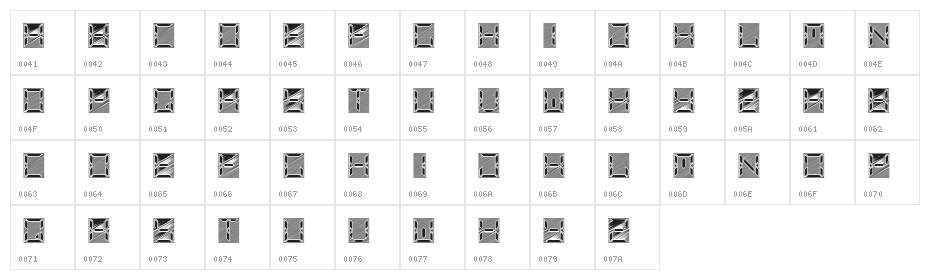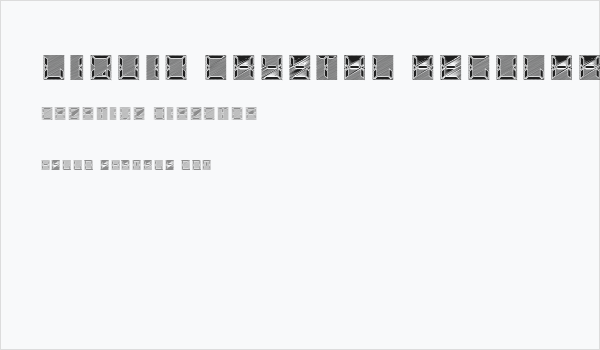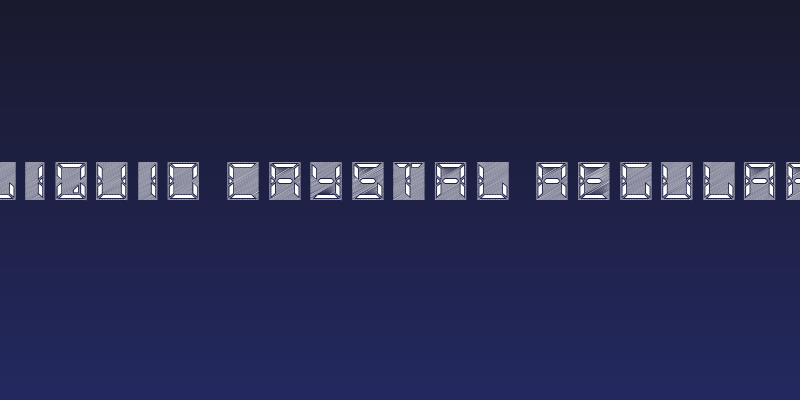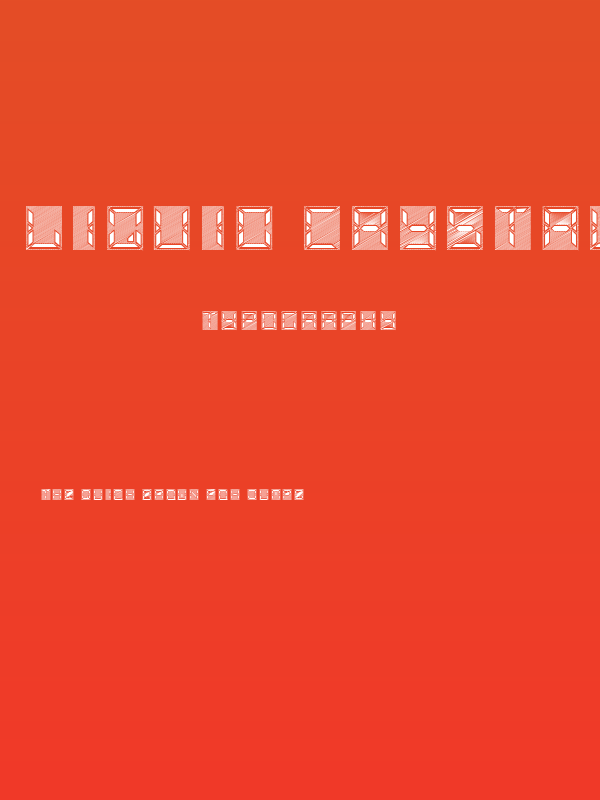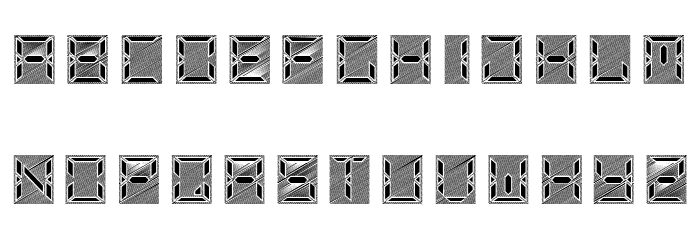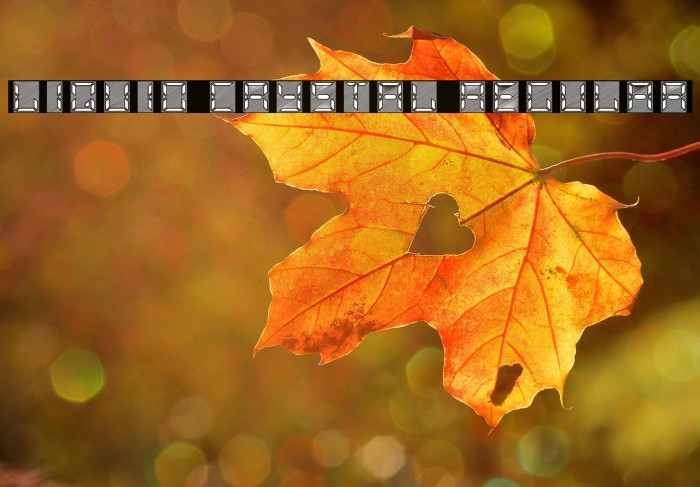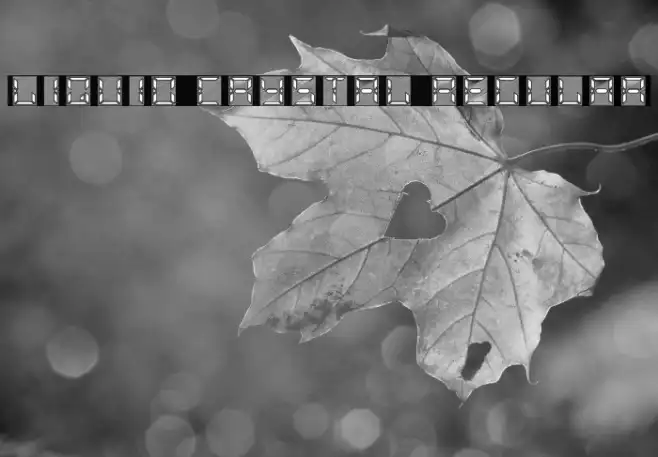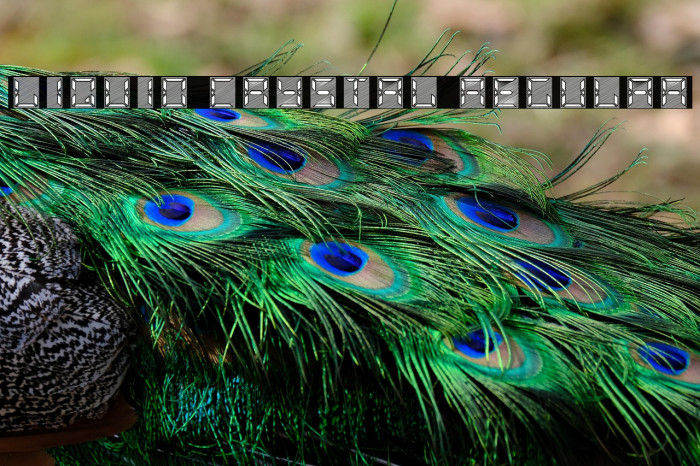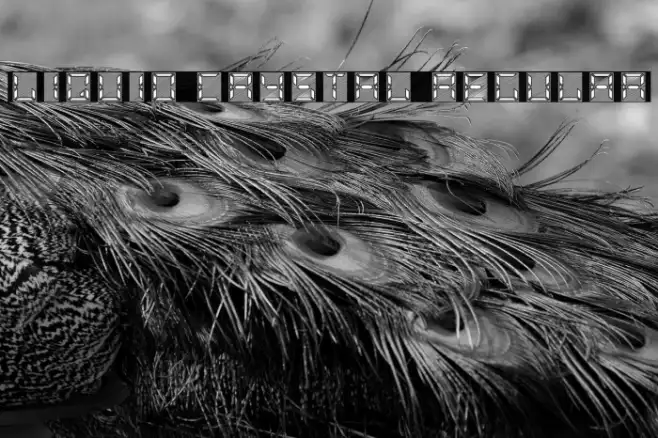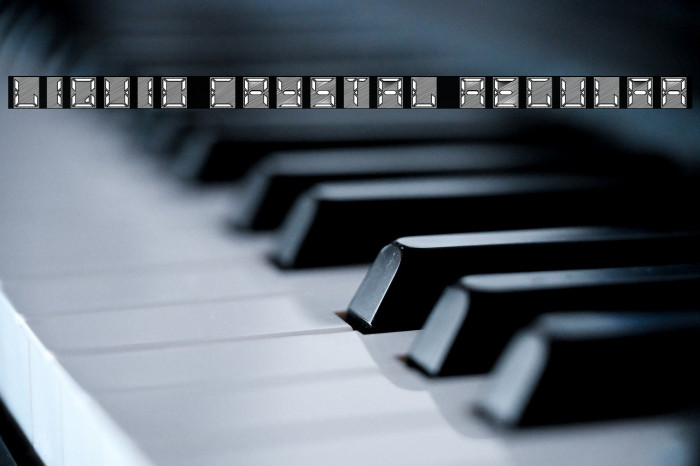
Liquid Crystal Regular Font
✎ Futuristic
| Kategorien | Futuristic |
| Gesamtstil | Futuristic |
| Anwendungsfall | Headlines, Logos, Digital Interfaces |
| Vorgeschlagene Projekte | Ideal for technology-themed projects, digital interfaces, sci-fi book covers, and modern branding. |